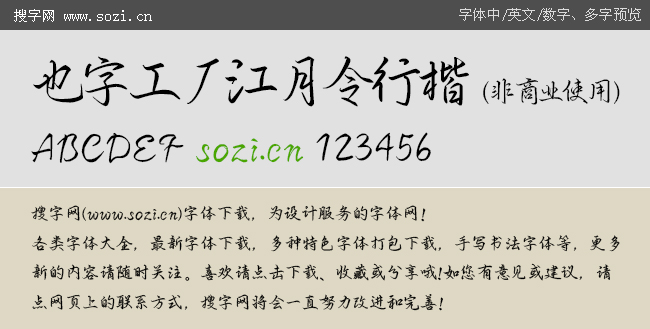
也字工廠江月令行楷
搜字網(wǎng)給大家提供一款也字工廠江月令行楷(非商業(yè)使用)中文字體下載,也字工廠江月令行楷是一款手寫書法字體,字體書寫流暢自然,字形瀟灑大方。具有很好的視覺(jué)效果。適合應(yīng)用于藝術(shù)設(shè)計(jì)、平面宣傳設(shè)計(jì)、網(wǎng)頁(yè)設(shè)計(jì)、海報(bào)設(shè)計(jì)等應(yīng)用(此字體為個(gè)人非商用版,商用可以聯(lián)系:官方網(wǎng)址:https://yefont.com/home,聯(lián)系方式:13798980448)。